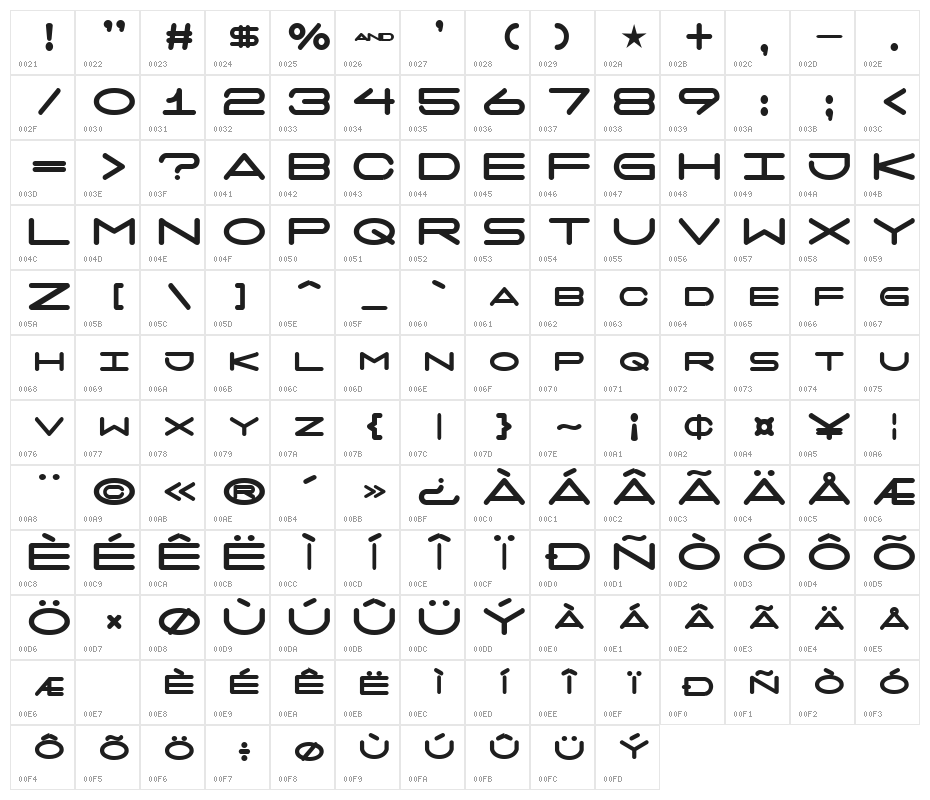
7 days fat Font
| Stile generale | Futuristic |
| Progetti proposti | Ideal for technology branding, sci-fi movie posters, video game titles, and modern web design. |